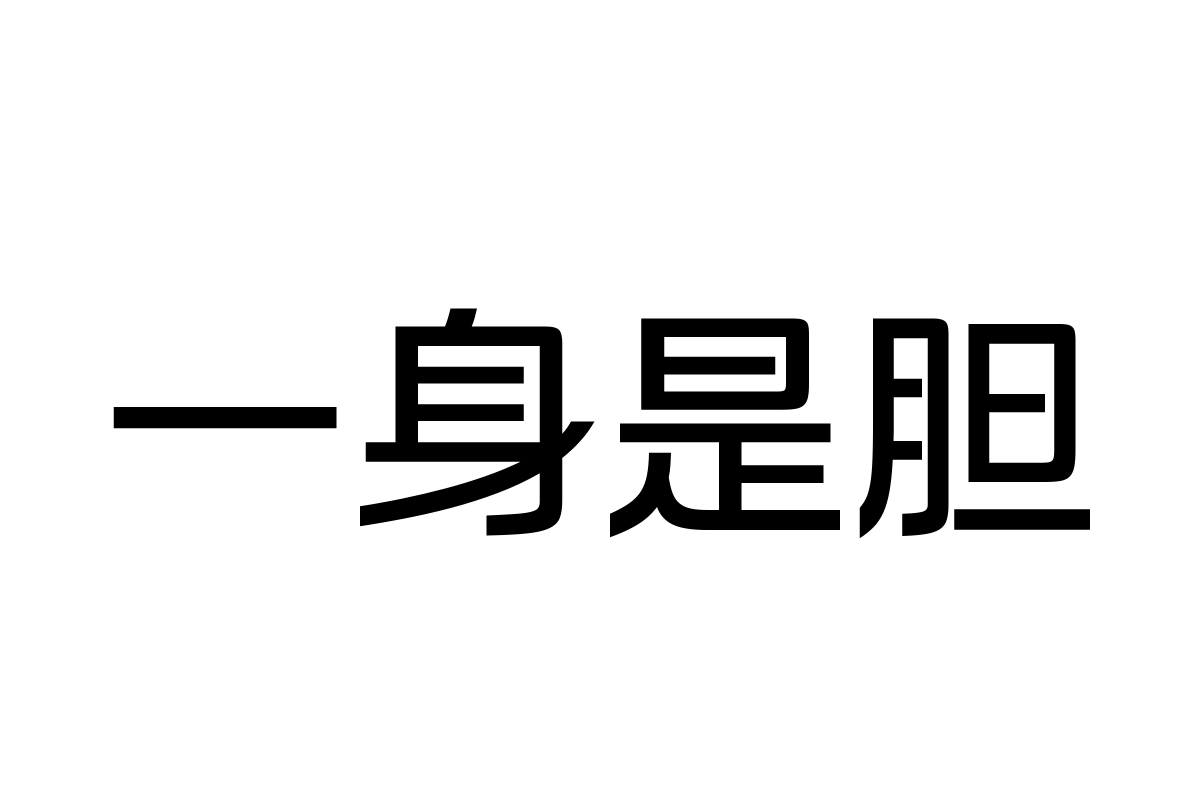
汉仪风尚黑是一款现代感十足的字体,具有独特的风格和特点。这款字体的特点是线条流畅、结构紧凑、笔画清晰,给人一种简洁、大方的感觉。它的字形设计采用了经典的楷书结构,但在细节上进行了优化和创新,使得整体效果更加和谐统一。
这款字体的笔画粗细适中,既不过于纤细也不过于粗壮,适合用于各种需要书写的场合。同时,它的字形大小也经过精心设计,既不会过大也不会过小,能够适应不同字体大小的需要。
此外,汉仪风尚黑还具有一定的艺术感和表现力,能够很好地传达出设计师想要表达的情感和意境。无论是用于文字排版还是图形设计,都能够展现出其独特的魅力和风格。
总的来说,汉仪风尚黑是一款非常适合现代设计需求的字体,无论是在商业广告、品牌宣传还是个人作品展示中,都能够得到很好的应用和效果。